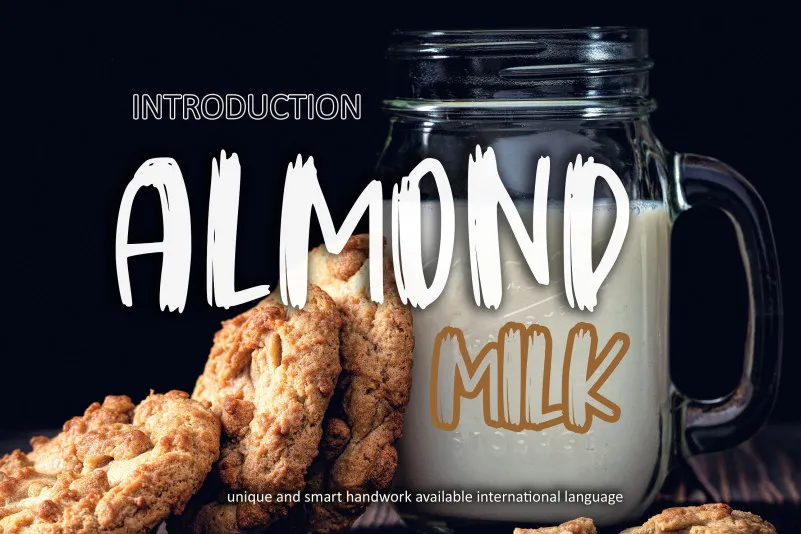
Almond Milk Brush Font – Download Grátis
A fonte ‘Almond Milk Brush Font’ é uma escolha perfeita para quem busca uma fonte agradável e amigável para trabalhos que exijam personalidade e estilo. Com um traço leve e aconchegante, essa letra brush pode dar vida a qualquer projeto de design gráfico, seja em logotipos, texturas ou ilustrações digitais. A fonte ‘Almond Milk Brush Font’ é ideal para quem deseja adicionar um toque de delicadeza e charme a seus trabalhos. Perfeita para expressar uma ideia elegante em um ambiente que não pode faltar personalidade. Com sua característica gráfica, essa fonte será uma incrível aquisição para qualquer biblioteca de fontes, tornando-a uma ótima opção para qualquer projeto que exija tanto charme quanto funcionalidade.